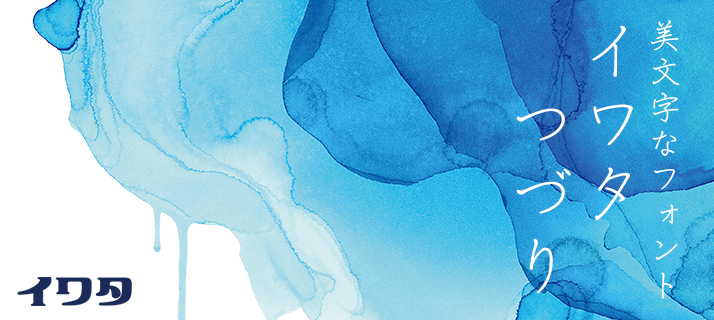
イワタより新書体「イワタつづり」の販売を開始しました!
この度、イワタから万年筆風フォントが誕生しました。
達筆な人がさらりと書いたような、明るくて読みやすいフォントです。
自由に色を変えられる通常のアウトラインフォントに加えて、万年筆のインクの濃淡を表現したカラーフォントも複数色ご用意しました。
丁寧な挨拶状からカジュアルなメッセージまで、さまざまなシーンにお使いいただけます。